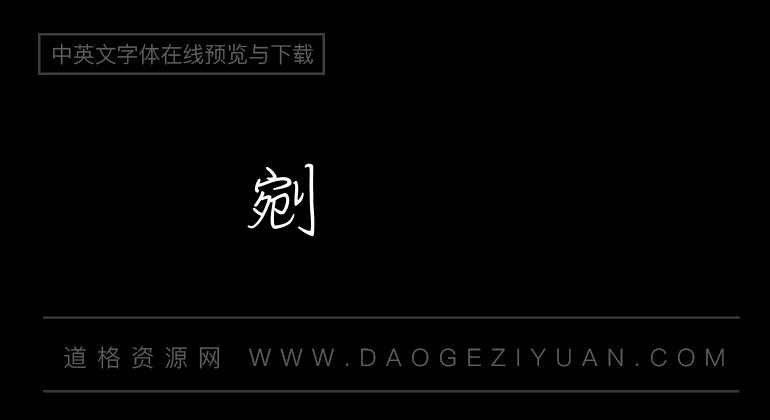
超研泽中钢笔行楷
超研泽中钢笔行楷字体是由超研泽工作室开发的中文楷体字体,它以中国传统楷体字体为基础,结合现代设计理念,融合了多种细节,形成了一种新的、更加精致的楷体字体。超研泽中钢笔行楷字体笔画细腻、结构严谨,丰富的字形让它具有更加优美的视觉效果,而且它还具有极高的可读性,能够更好地满足文字的可视化表达需求。
超研泽中钢笔行楷是一款非常不错的手写艺术字体,具有很好的视觉感,适合于文化类的宣传设计、商业类品牌的广告和产品包装设计以及个性化文字排版等较多场景。